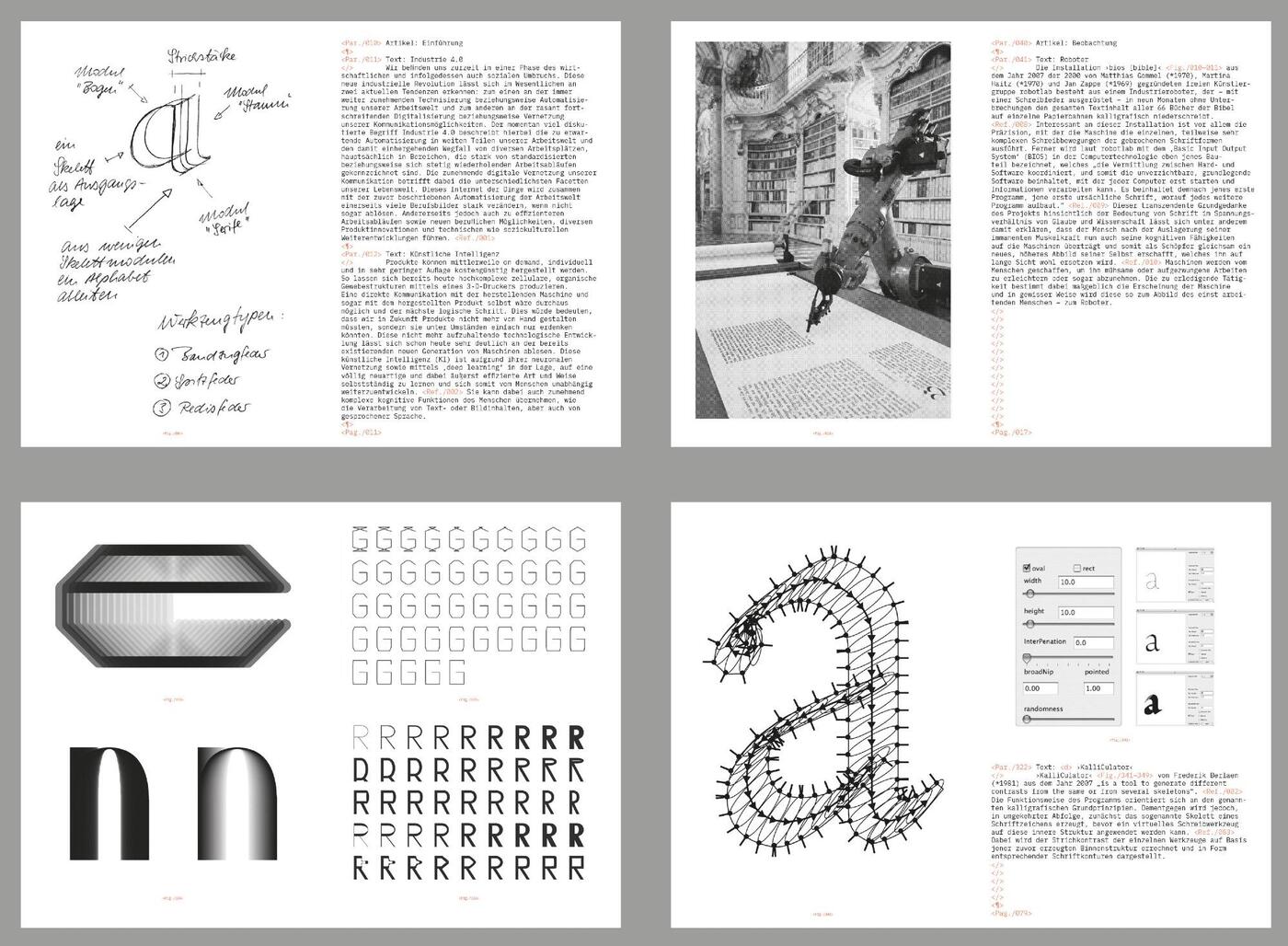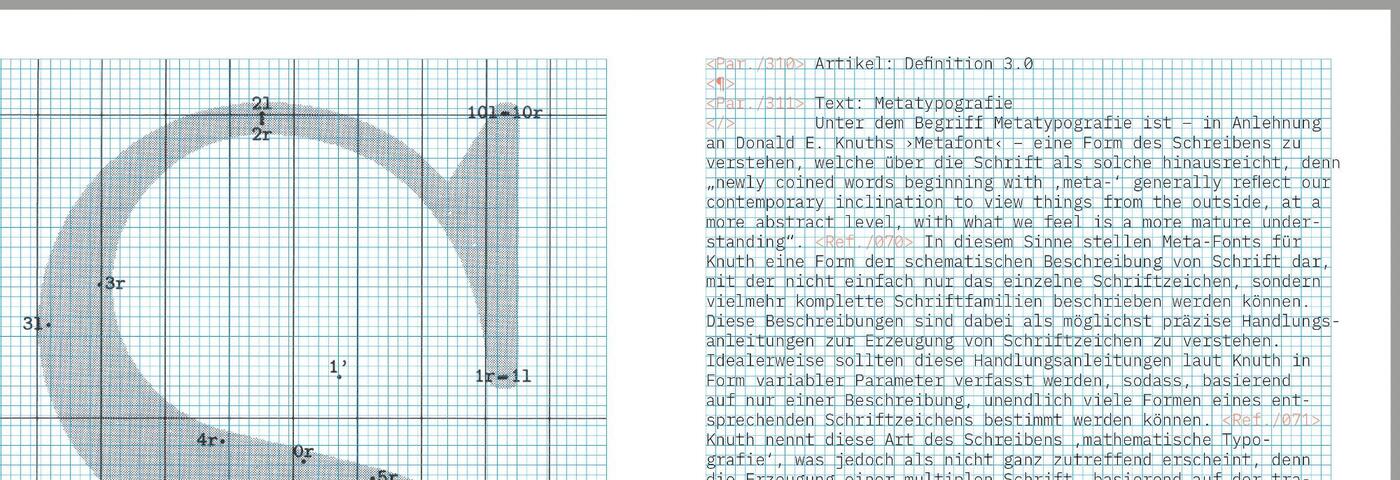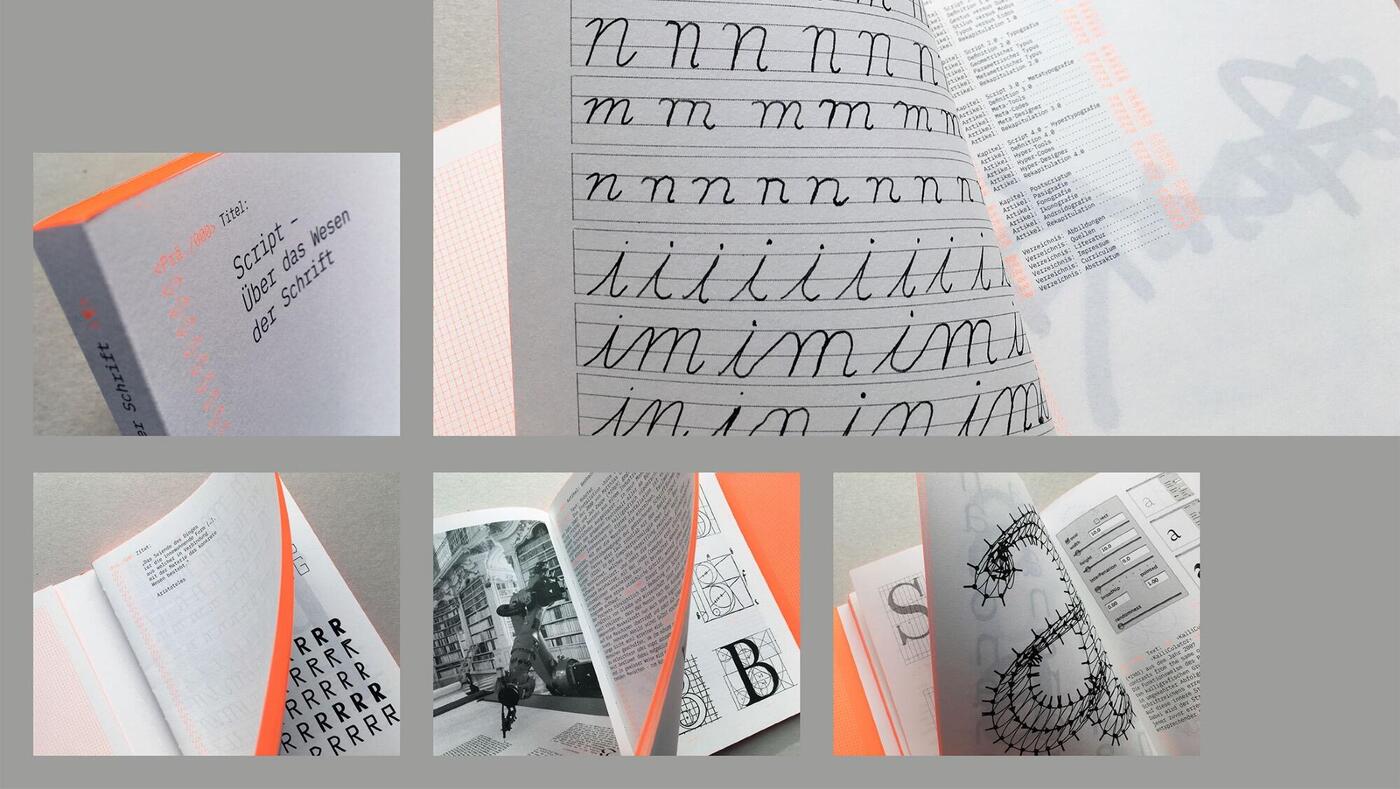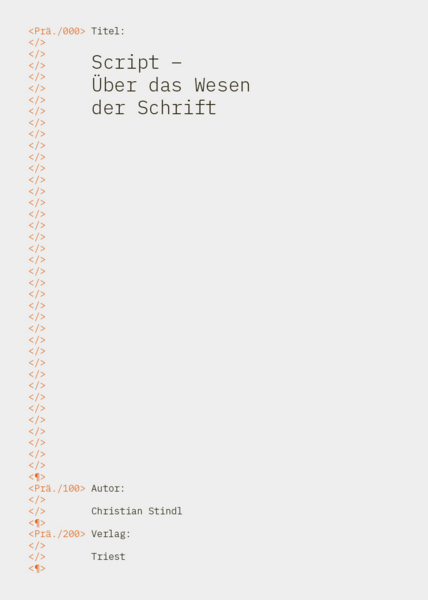
Script: Über das Wesen der Schrift
Aus der Verlagsbeschreibung:
»Unsere bestehenden Schriftsysteme gehören zu den bedeutendsten soziokulturellen Errungenschaften – die Schrift beeinflusste sowohl unser Denken als
auch Handeln maßgeblich. Die aktuellen technologischen Veränderungen – Internet der Dinge, Industrie 4.0, KI – erfordern aber einen strukturellen Wandel, der sich in der Art und Weise, wie wir denken, kommunizieren und produzieren, niederschlagen wird.
Mit diesem Positionspapier eröffnet der Autor einen Diskurs hinsichtlich der aktuell gängigen Praxis im Bereich der Gestaltung von Schrift. Er kritisiert dabei die offenkundige Diskrepanz zwischen der stetig zunehmenden Anzahl an formellen Neuinterpretationen von Schriftzeichen einerseits sowie der mangelnden strukturellen Reflexion des lateinischen Zeichensystems. Christian Stindl begibt sich auf die Suche nach dem Wesen der Schrift der Zukunft. Er hinterfragt ihre heutige Relevanz und prognostiziert gleichsam
den Untergang des lateinischen Zeichensystems. Ein grundsätzliches Umdenken seitens der Schriftgestalter sowie eine notwendige Neuausrichtung dieser Disziplin sind daher seiner Ansicht nach unbedingt erforderlich.«
Das durchgängig zweifarbig in schwarz und orange gestaltete Buch blickt zunächst in den ersten beiden auf die bisherige Entwicklung zurück. Der Bogen wird dabei von der Kalligrafie – über die Einführung der Typografie – bis hin zu neuen Entwicklungen wie variablen Fonts gespannt. Im Gegensatz zu den Rückblicken in anderen Typografie-Büchern liegt der Fokus hier aber ausdrücklich auf der Struktur und dem Entwurf der Schrift.
Der Rückblick in den ersten beiden Kapiteln mündet dann in einer (Auf-)Lösung und einem Ausblick in den Kapiteln drei und vier. Den klassischen Schriftentwürfen der letzten Jahrhunderte wird ihre eher statische und wenig innovative Entwurfsform vorgeworfen und dabei werden auch moderne Entwicklungen wie interpolierte Schriften und Zufallssysteme wie zum Beispiel bei der FF Beowolf ausdrücklich eingeschlossen. Das Kapitel Meta-Typografie bietet dann dafür den vorgeschlagenen Ausweg mit Lösungen wie dem eher »programmierten« Metafont-Format innerhalb des TeX-Systems, das dem Schriftnutzer »unendliche Möglichkeiten« offenbaren soll.
Im letzten Kapitel wird dann über eine mögliche Zukunft der Schrift spekuliert, wobei die Artikel hier (vielleicht naturgemäß) recht vage bleiben. Angeführt werden hier Aussagen von Philosophen wie Vilém Flusser und Schriftexperiemente, die interessanterweise aber vornehmlich aus dem künstlerischen Bereich stammen.
Einschätzung: Der Rückblick auf Entwicklung des Schriftentwurfs aus struktureller Hinsicht ist durchaus interessant und mag für heutige Schriftanwender lehrreiche Details beinhalten. Ansonsten ist das Buch trotz des beschreibenden und stellenweise zitatlastigen Stils einer akademischen bzw. kulturwissenschaftlichen Arbeit aber wie im Klappentext versprochen ein »Positionspapier«. Dem Leser wird eine recht klare Wertung aufgedrängt und damit macht es sich das Buch leider für meinen Geschmack zu einfach. Es stellt nicht Positionen gegenüber, sondern lässt nur eine Lesart zu. Schriftgestaltern wird pauschal und sehr deutlich eine »mangelnde Reflexion« unterstellt, wenn sie den Kanon der Schriftstile immer weiter ausdifferenzieren und Schrift nicht grundsätzlich neu erfinden. Mögliche Gründe für die Motivation der Schriftgestalter werden aber nicht hinterfragt oder thematisiert. So lässt das Buch hier ironischerweise selbst etwas Reflexion vermissen. In gleichem Sinne wird dann das Metafont-System und ähnliche, auf Programmierung aufgebaute Fontsysteme eher einseitig gelobt, ohne deren Grenzen und Probleme aufzuzeigen, die womöglich erklären könnten, warum diese Systeme bis heute ein Nischendasein fristen.
Dabei müsste die im Buch heraufbeschworene Kontroverse um die Struktur und damit das »Wesen« der Schrift ja vielleicht gar keine sein. Die im Buch herausgestellten künstlerischen, experimentellen und mathematischen Ansätze zum Einsatz von Schrift, für die der Autor offenbar zu schwärmen scheint, können mit Schrift als ein Konventionen unterworfenem, aber gerade deswegen massentauglichem Kommunikationsmittel einfach koexistieren.